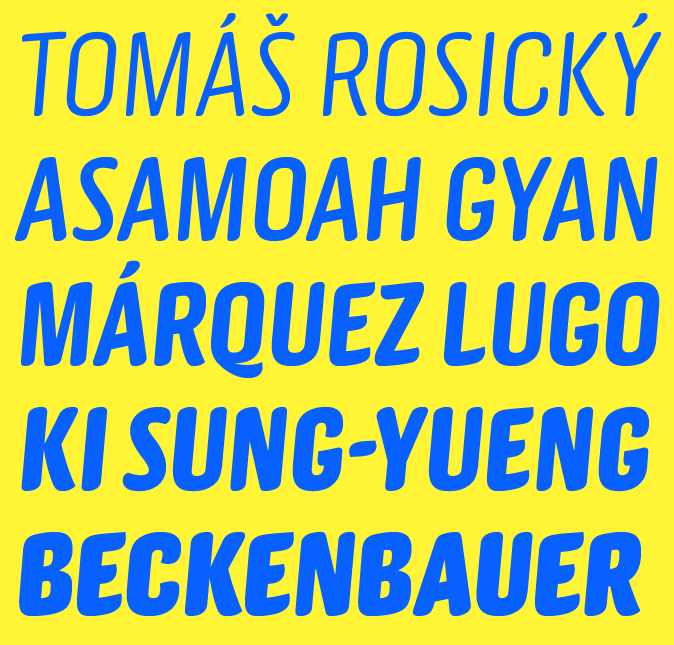
| Año | 2014 |
| Cliente | Puma (US) |
| Despacho / Estudio | Commercial Type |
| Diseñador | Miguel Reyes • Paul Barnes |
| Otros créditos | TDC winner 2008. Selección Tipos Latinos 2008 |
Gabriello fue encargada por Puma. Primero fue usada para los uniformes en los equipos de la Africa Cup of Nations 2010, incluyendo a Egypto, ganador del torneo y después fue usada en los uniformes de la copa del mundo en Sudáfrica.